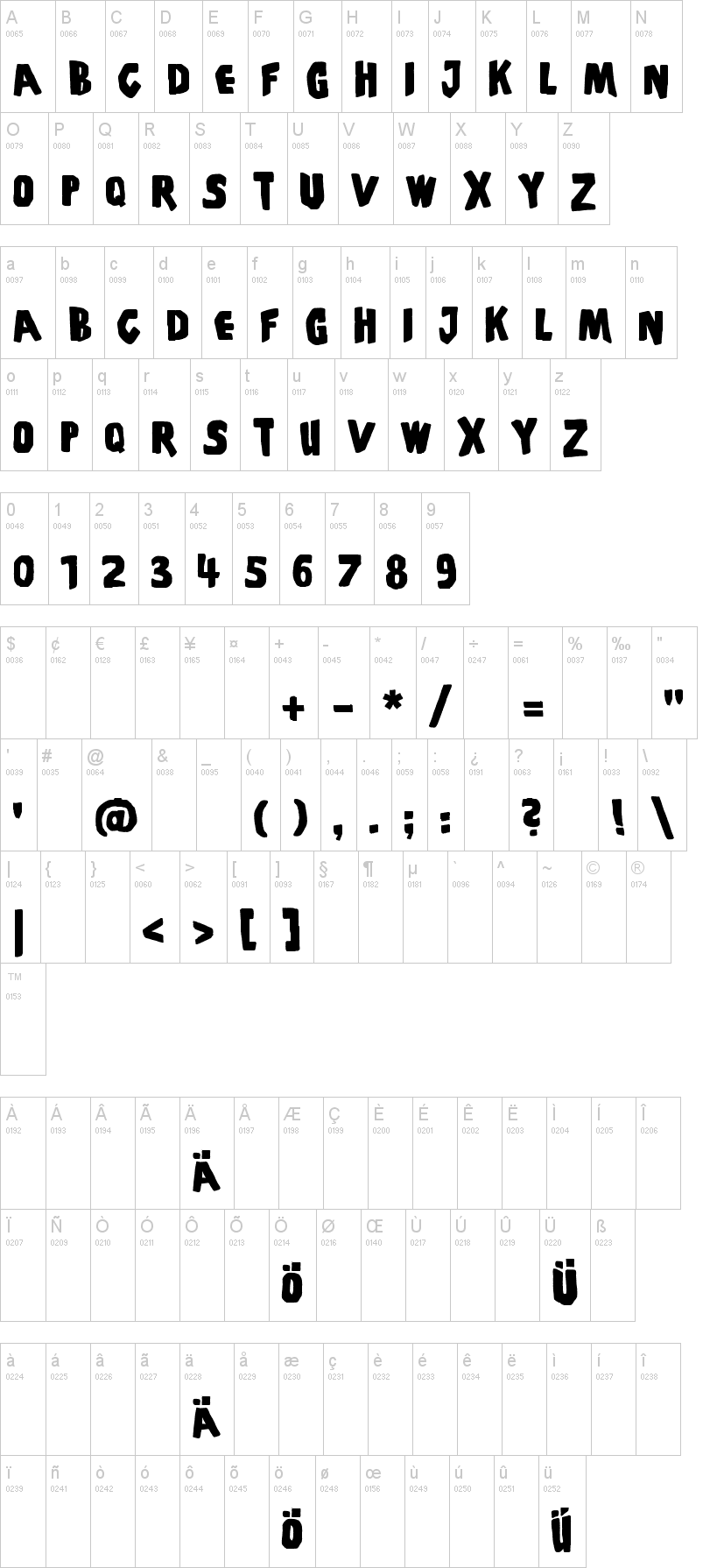
? PiS Coffins and Ghosts 字体是一款古老而又神秘的英文字体,它由英国设计师Paul Lloyd-Smith设计,特色是拥有粗犷的线条和古老的韵律,它可以营造出一种极具幽默感的氛围,适合用来表达恐怖、科幻、悬疑等主题。内容介绍
PiS Coffins and Ghosts是一款非常不错的手写艺术字体,具有很好的视觉感,适合于文化类的宣传设计、商业类品牌的广告和产品包装设计以及个性化文字排版等较多场景。